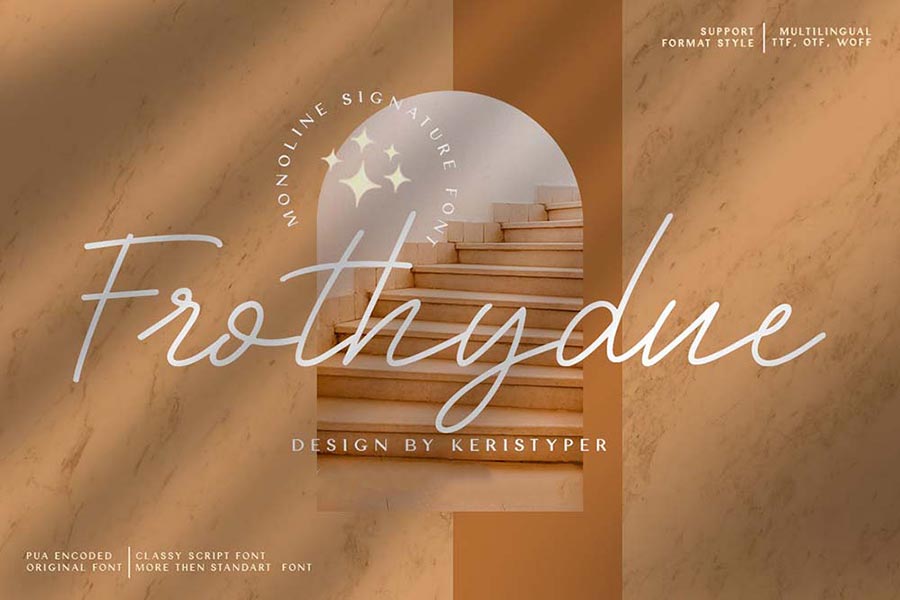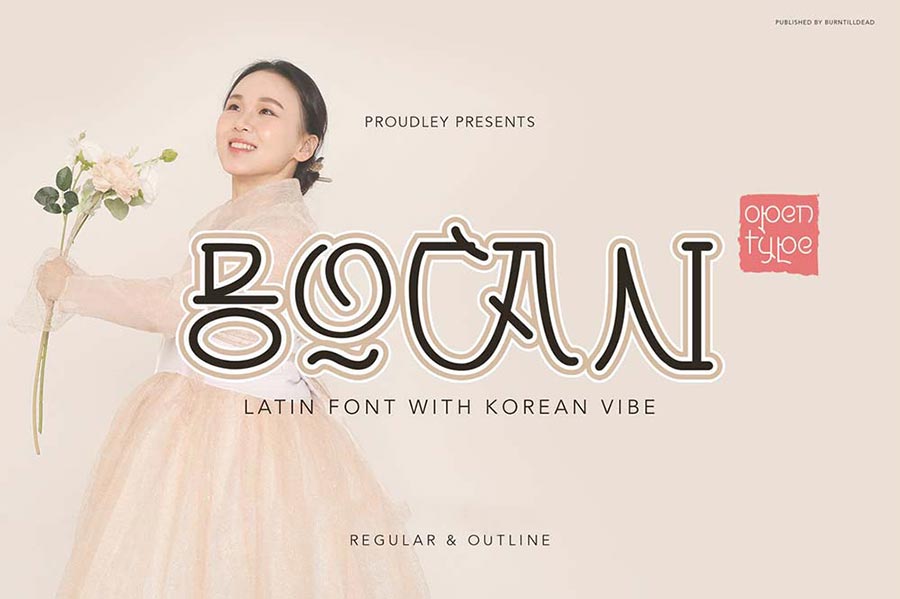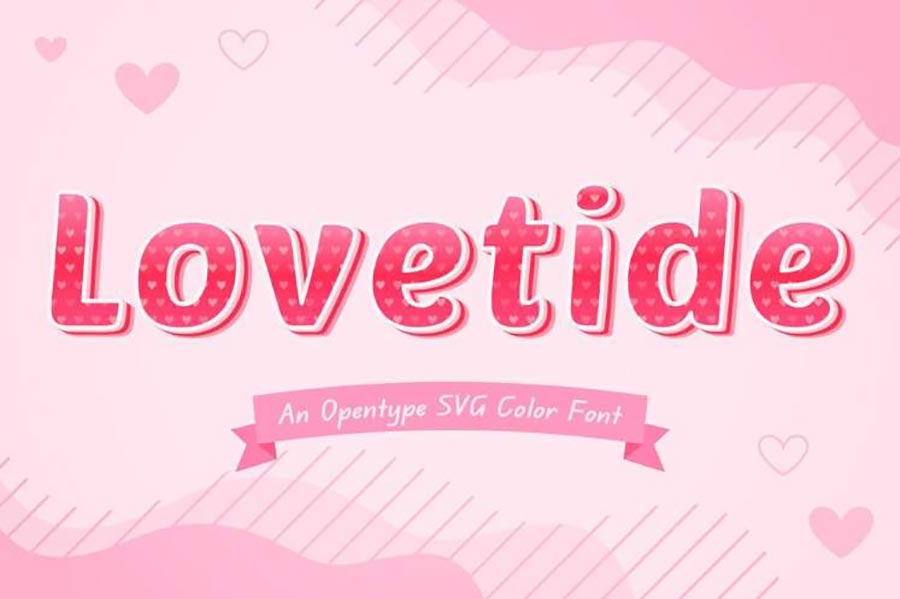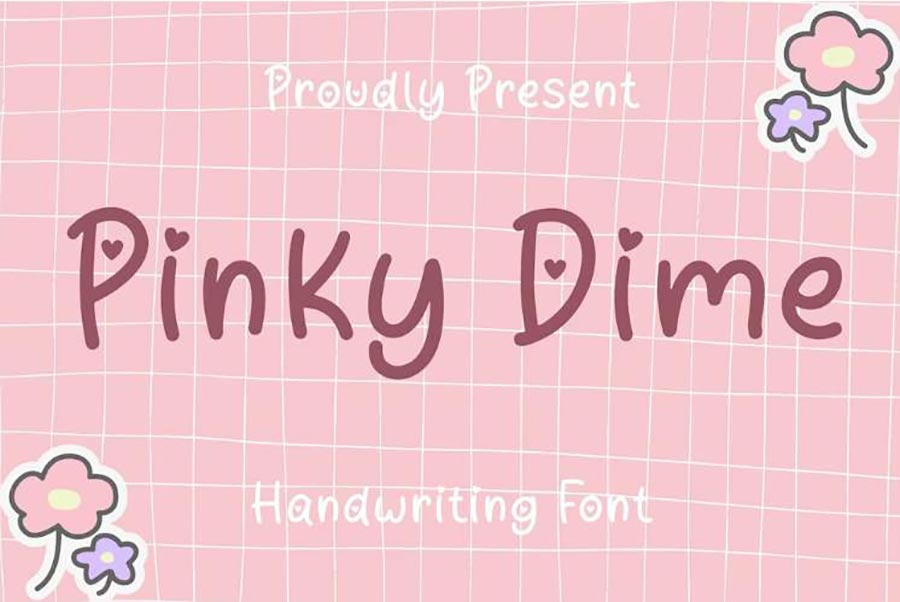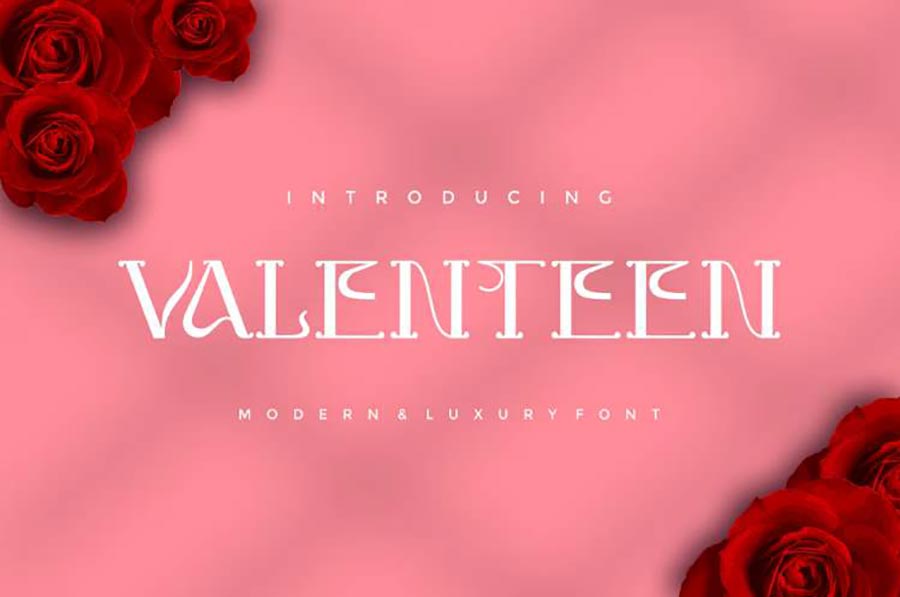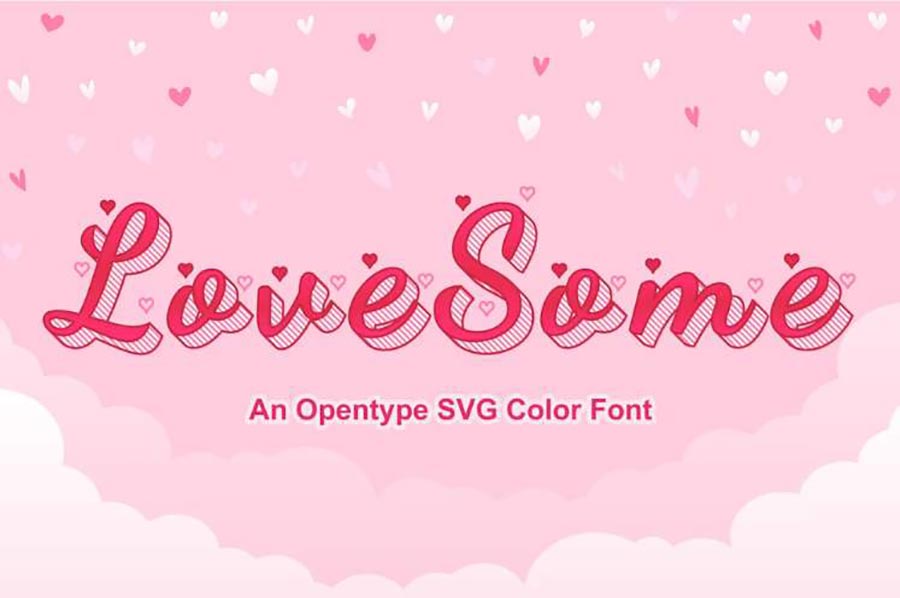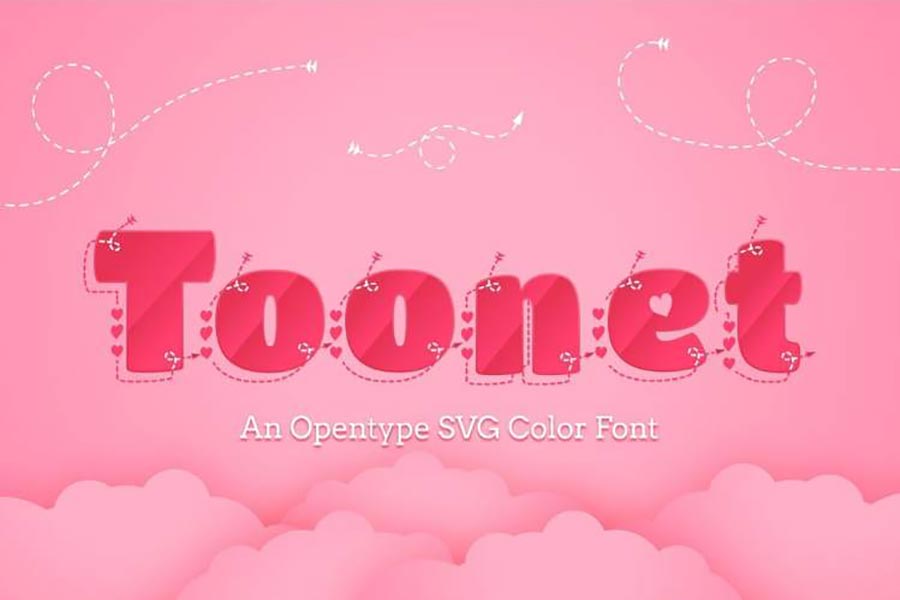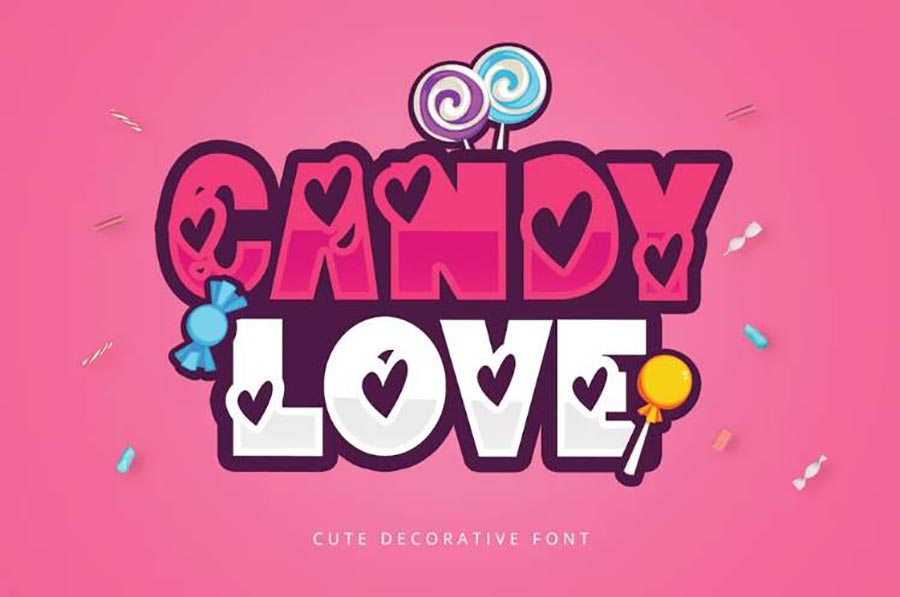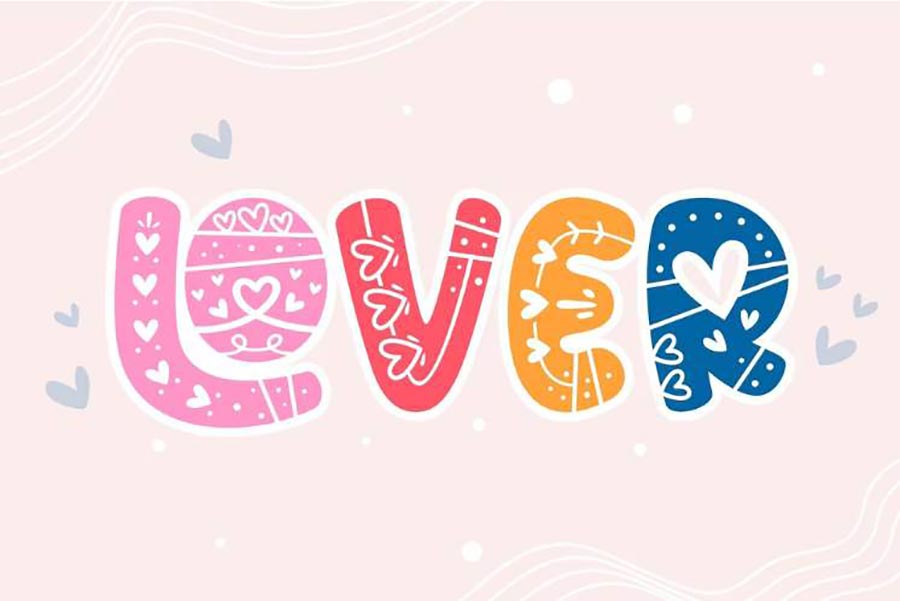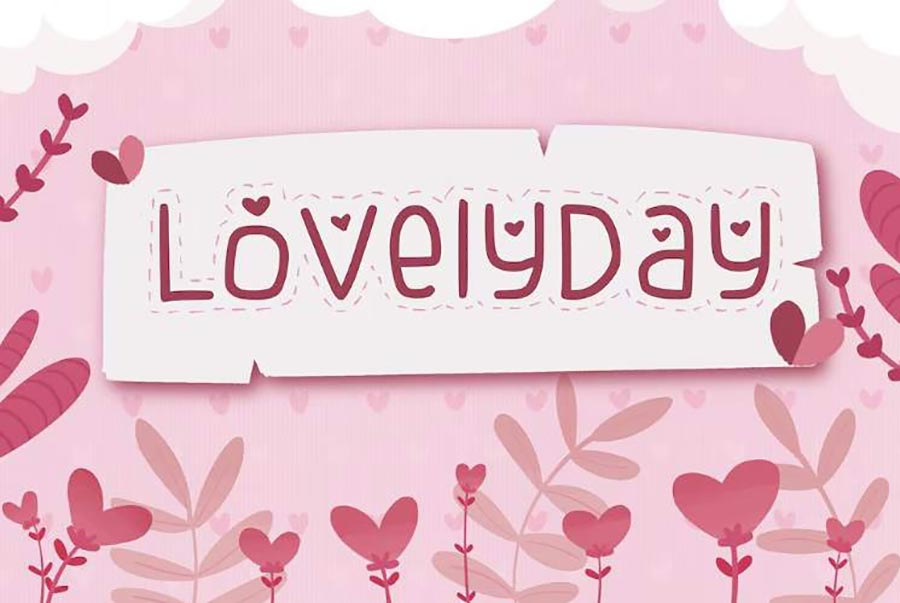
Mùa Valentine đang đến gần, và việc tạo ra những thiết kế ấn tượng, lãng mạn chính là cách để bạn thể hiện tình yêu trong từng sản phẩm. Một trong những yếu tố quan trọng nhất để truyền tải cảm xúc đó chính là font chữ. Hôm nay, Sadesign.vn sẽ giới thiệu đến bạn bộ sưu tập 15+ fonts Valentine's Day tuyệt đẹp miễn phí, giúp bạn tạo ra những thiết kế thật đặc biệt cho ngày lễ tình nhân. Trong bài viết này, chúng tôi sẽ hướng dẫn bạn cách tải bộ font này và sử dụng chúng hiệu quả trong các dự án thiết kế của mình.
Bộ 15+ Fonts Valentine's Day Miễn Phí Là Gì?
Bộ fonts Valentine's Day tại Sadesign.vn là một bộ sưu tập đặc biệt với hơn 15 kiểu chữ được thiết kế riêng cho mùa lễ tình nhân. Các fonts này mang đậm nét lãng mạn, dễ thương và đầy sự sáng tạo, phù hợp với các dự án thiết kế liên quan đến Valentine, từ thiệp mời, poster, banner, đến các sản phẩm quà tặng, logo, và nội dung mạng xã hội.
Với bộ fonts này, bạn sẽ dễ dàng tạo ra những sản phẩm vừa ấn tượng, vừa thể hiện được tình yêu và sự ngọt ngào của mùa lễ hội.
2. Phong Cách Lãng Mạn: Các font chữ đều mang phong cách dễ thương, ngọt ngào, hoàn hảo cho các dự án Valentine.
Ứng Dụng Bộ 15+ Fonts Valentine's Day Trong Thiết Kế:
Bộ fonts Valentine's Day của Sadesign.vn có thể áp dụng vào rất nhiều loại hình thiết kế, từ đơn giản đến phức tạp. Dưới đây là một số gợi ý giúp bạn tận dụng bộ fonts này một cách hiệu quả:
1. Thiết Kế Thiệp Valentine: Tạo ra những tấm thiệp Valentine độc đáo, lãng mạn để gửi đến những người bạn yêu thương, sử dụng các font chữ mềm mại và dễ thương.
2. Quảng Cáo Mùa Valentine: Sử dụng fonts này để thiết kế poster, banner hoặc chiến dịch email marketing cho các cửa hàng quà tặng, hoa tươi, hay các sự kiện đặc biệt trong mùa lễ tình nhân.
3. Sáng Tạo Nội Dung Trên Mạng Xã Hội: Chia sẻ các câu chúc mừng Valentine trên Instagram, Facebook với những font chữ lãng mạn, thu hút sự chú ý của người xem.
4. Thiết Kế Quà Tặng In Ấn: Bạn có thể sử dụng các font này để tạo ra thiết kế cho các sản phẩm in ấn như áo phông, cốc, móc khóa, v.v., đặc biệt là trong dịp lễ Valentine.